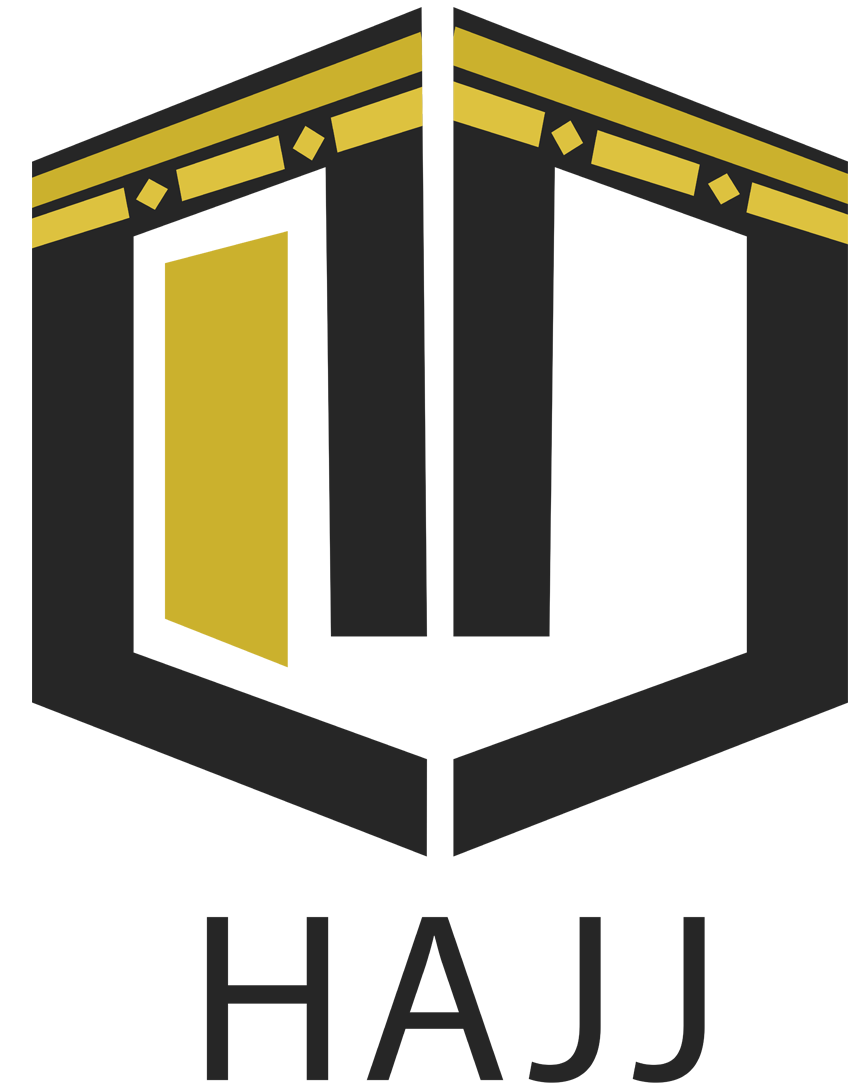
معاينة الخط مخطوطة وشعار للحج - ملونة اضغط هنا لتحميل الخط
| الوصف : مخطوطة على شكل شعار او logo لكلمة الحج ,, ملونه وفرغه وبدقة عالية جدا ,, لتصاميمك لمناسك الحج ويوم عرفة